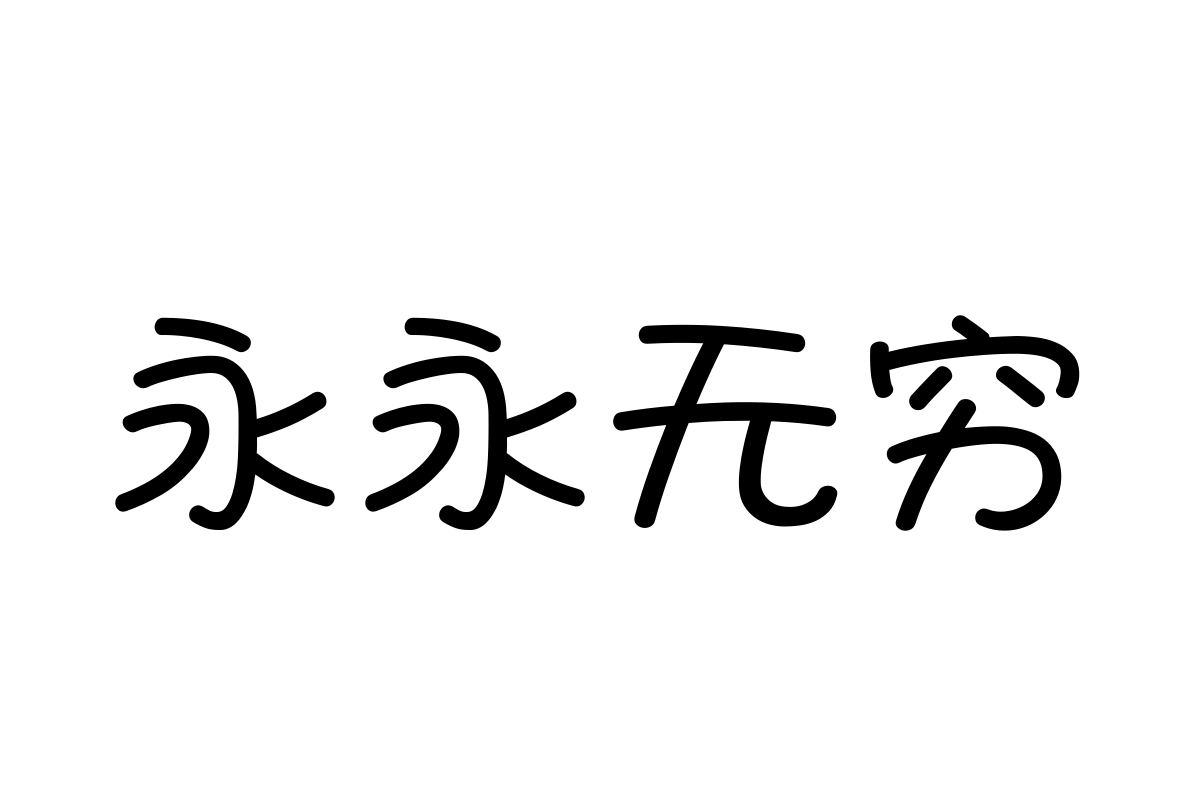
字体管家胖丫儿体是一款由字体管家团队开发的字体,具有独特的设计风格和特点。这款字体的笔画粗细适中,线条流畅,给人一种优雅而自然的感觉。同时,它的字形结构紧凑,整体呈现出一种饱满而有力的视觉效果。
胖丫儿体的特点在于其圆润的字形和可爱的风格。这种字体的设计灵感来自于胖嘟嘟的卡通形象,因此给人一种亲切而可爱的感觉。无论是用于儿童插画、漫画作品还是其他需要可爱风格的设计,胖丫儿体都能展现出其独特的魅力。
此外,胖丫儿体还具有一定的可读性。由于其笔画粗细适中,线条流畅,因此在日常阅读中能够清晰地呈现文字内容。同时,它的字形结构紧凑,整体呈现出一种饱满而有力的视觉效果,使得阅读体验更加舒适。
总的来说,字体管家胖丫儿体是一款具有独特风格和特点的字体,适合用于需要可爱风格和可读性的应用场景。